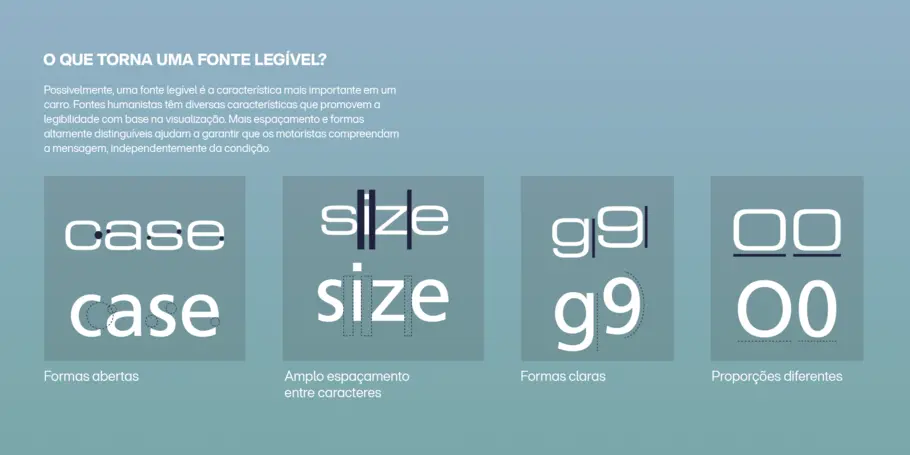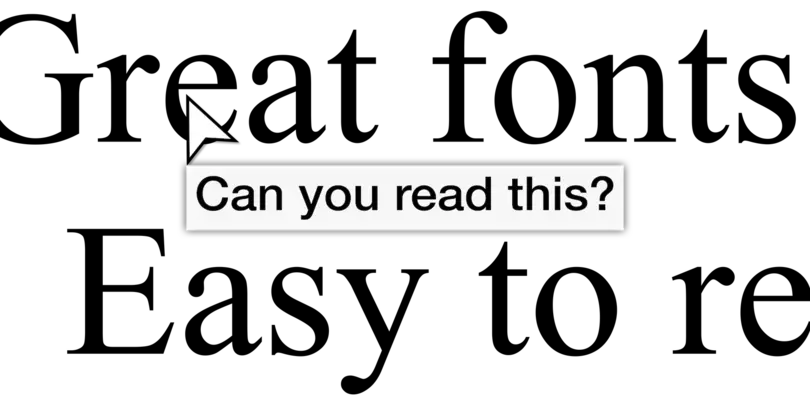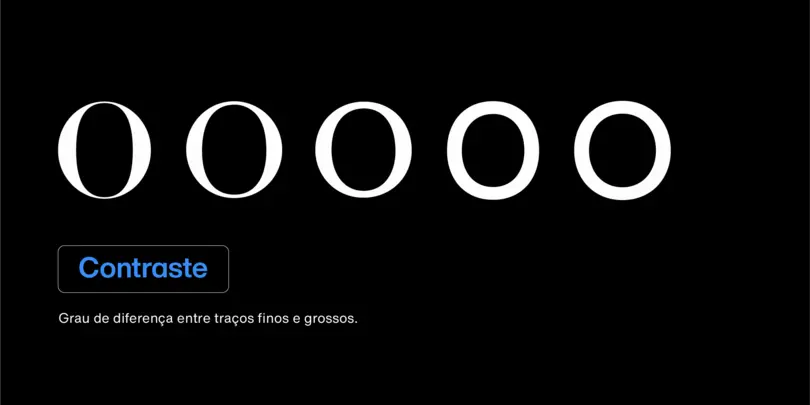
Como encontrar fontes legíveis.
“ Como muitas questões de design, a receita para essa resposta é uma mistura de arte e ciência e é regida por menos regras do que por melhores práticas. O segredo é compreender os principais componentes de uma fonte que afetam a legibilidade. ”
A legibilidade é uma consideração crucial ao tentar escolher uma fonte para o seu projeto. Veja como encontrar uma fonte legível que seja agradável aos olhos de seus leitores e clientes.
Recebemos muitas perguntas aqui na Monotype, mas uma das mais frequentes é provavelmente alguma variação disso: como encontro fontes legíveis? As pessoas podem perguntar de forma diferente — perguntarão quais fontes são mais legíveis, por exemplo, como saber se uma fonte é altamente legível — mas todos estão perguntando a mesma coisa básica: o que torna uma fonte legível e como faço para encontrar uma?
Como muitas questões de design, a receita para essa resposta é uma mistura de arte e ciência e é regida por menos regras do que por melhores práticas. A chave é compreender os principais componentes de uma fonte que afetam a legibilidade e, em seguida, encontrar a fonte com as características que melhor correspondem à linguagem visual com a qual você está trabalhando.
Legibilidade é um tópico amplo com muito mais nuances do que podemos abordar em um único artigo, mas compreender alguns pontos-chave ajudará você a escolher com segurança uma fonte legível para seu próximo projeto. Então, vamos nos aprofundar!
Easy to Read
A legibilidade está na mente do leitor.
Quando lemos, nossos olhos captam as formas escritas em uma página, traduzem essas formas em letras, combinam as letras em palavras e depois conectam essas palavras aos seus significados. Tudo isso acontece tão rapidamente que mal percebemos.
Mas, se uma dessas etapas do processo ficar mais lenta ou encontrar um obstáculo, nossa leitura também fica mais lenta. Isso pode não importar em alguns casos – uma manchete deliberadamente ofuscada em uma revista, talvez – mas é muito importante em casos de uso digital ou de rápida visualização, ou em ambientes de leitura estendida em que você deseja que o leitor mergulhe na história.
Fontes altamente legíveis essencialmente fogem da atenção do leitor. Elas são fáceis de serem examinadas pelos olhos e de compreensão pelo cérebro, de modo que o leitor é capaz de fluir pelas páginas de um livro ou verificar instantaneamente o texto na tela de um carro. Eles podem parecer tão naturais e fáceis quanto respirar.
O que torna uma fonte legível?
Certo, então a pergunta óbvia aqui é: o que torna uma fonte “fácil” para os olhos e o cérebro? Todas as fontes não são só… letras? Por que algumas cartas são mais fáceis de ler do que outras?
Ao procurar fontes legíveis, é útil pensar no formato das letras e das palavras (curiosidade: o termo para o formato da palavra é “bouma”). Na verdade, seus olhos e seu cérebro não traçam cada curva e ângulo de um “a” minúsculo antes de confirmar que, sim, é um “a” minúsculo. Talvez seja assim que funcionava quando você estava aprendendo a ler. Ainda assim, a maioria de nós ganha a capacidade de determinar que um “a” é um “a” com base na sua forma geral e na sua relação com as letras que estão ao lado.
Dito isso, as letras vêm em uma variedade de formatos, dependendo do estilo da fonte. O “O” em uma sem serifa geométrica, como ITC Avant Garde, é um círculo quase perfeito. Só um “a” poderia ser confundido, a princípio, com o mesmo “o”. Você consegue ler sans geométricos como Avant Garde ou Futura? Claro. Mas, muitas vezes, poderia ser mais fácil.
Insira fontes humanistas. Frederic Goudy. As fontes humanistas estão enraizadas na tradição caligráfica e, portanto, têm ecos na tipografia humanista (daí o nome) gravadas em seu DNA. Um exemplo popular de tipo humanista é Proxima Nova, de Mark Simonson. Olhe atentamente para o “o” e você verá que ele tem um formato oval sutil, não um círculo. Examine o “a” minúsculo e você notará que os traços na cavidade ficam mais finos à medida que encontram a haste vertical. Todos esses detalhes sinalizam a identidade da letra para nossos cérebros. Outras tipografias humanistas populares (e híbridos humanistas/geométricos) incluem Frutiger, Morandi, Gotham e Optima.
As fontes serifa oferecem legibilidade semelhante ao leitor, por isso não é surpresa que sejam a escolha predominante para livros, revistas e outras situações de leitura de formato longo. No entanto, as fontes com serifa têm historicamente representado um desafio em casos de uso digital devido ao contraste do traço, a diferença entre linhas grossas e finas em uma fonte (discutida abaixo). Fontes com serifa de alto contraste de traços com linhas finas são destinadas ao uso em tamanhos maiores, enquanto as serifas destinadas ao uso em tamanhos menores são projetadas com menos contraste de traços. Esse efeito e complexidade são frequentemente exacerbados pela qualidade da tela, o que torna as fontes com serifa mais difíceis de serem projetadas em casos de uso digital em que uma variedade de tamanhos pode ser necessária. Por causa disso, as tipografias humanistas se tornaram a escolha preferida para casos de uso digital e assim permanecem até hoje, embora as telas móveis modernas ofereçam clareza quase perfeita em fontes com serifa.
Um bom exemplo do oposto desses estilos é a fonte Eurostile. Não há nada de errado com o Eurostile como fonte e, na verdade, ela é incrivelmente popular em filmes de ficção científica por causa de sua vibe futurista (nos anos 70) e agora retro-futurista. Quando as montadoras começaram a implementar touchscreens e sistemas de infoentretenimento em seus veículos, muitas delas escolheram o Eurostile para a experiência do usuário desses sistemas. O Eurostile é amplamente baseado em letras quadradas que podem ser difíceis de distinguir umas das outras quando você tem apenas uma fração de segundo para observá-las. Como quando você está dirigindo um carro, por exemplo.
2001_eurostile_63_0
Características de uma fonte legível.
Encontrar uma fonte legível é uma questão que requer analisar muitos aspectos e, essencialmente, o objetivo é encontrar uma fonte que seja confortável de ler. Para os designers, o segredo é entender alguns detalhes essenciais que contribuem para uma boa legibilidade e, então, encontrar fontes que equilibrem esses fatores com a linguagem visual que você procura.
Contraste:
o contraste descreve a diferença entre traços grossos e finos em uma letra. Fontes com algum contraste são geralmente mais fáceis de ler porque a variação na largura do traço ajuda o leitor a distinguir entre letras que têm formatos comuns.
Dito isso, fontes com muito contraste podem acabar sendo bastante difíceis de ler fora dos usos de exibição. Uma fonte como Bodoni, com sua dinâmica espessa dramática e fina, cria um título impressionante. Mas esses traços finos e delicados praticamente desaparecem no tamanho do corpo do texto, tornando o tipo de letra praticamente impossível de ler.
Contraste
Altura-X:
a Altura-x refere-se literalmente à altura do x minúsculo em uma fonte, o que essencialmente determina a altura das letras minúsculas na fonte. Alturas-x maiores tendem a proporcionar melhor legibilidade porque o tamanho generoso torna as letras mais fáceis de ler.
No entanto, a altura-x muito alta pode confundir a distinção entre caracteres maiúsculos e minúsculos e até mesmo entre certos caracteres minúsculos (h e n, por exemplo). Alturas-x pequenas também podem proporcionar boa legibilidade, dependendo do design e do peso da fonte.
Espaçamento, kerning e crowding em geral:
o espaço entre as letras é tão essencial para a legibilidade quanto as próprias letras. Um r e n com kerner incorreto, por exemplo, podem facilmente parecer um m. O texto muito compacto em geral pode atrasar o leitor, e o texto muito solto pode aparentemente sair da página.
Algumas fontes são espaçadas e com kerner cuidadosamente pensado e precisam de poucos refinamentos adicionais, mas muitas exigirão ajustes cuidadosos quando colocadas no layout. O tipo legível deve parecer que respira e flui facilmente, guiando o leitor através de palavras e frases sem olhar duas vezes.
Durante o processo de descoberta, procure fontes em que as letras estejam conectadas, mas não aglomeradas e, se possível, investigue combinações de letras potencialmente problemáticas para problemas de kerning. Isso ajudará você a determinar quanto ajuste precisará fazer sozinho.
Dimensionamento óptico:
o dimensionamento óptico é a prática de projetar diferentes versões de uma fonte levando em consideração como e onde ela será experimentada. Essas otimizações podem incluir muito do que foi discutido acima – ajuste de espaçamento, altura-x, contraste do traço ou detalhes. Tamanhos maiores são projetados tendo em mente usos chamativos – manchetes ou até mesmo outdoors – e, normalmente, mostram os detalhes e sutilezas de um tipo de letra, ao mesmo tempo que espaçam adequadamente para escalas maiores. Por outro lado, os formatos das letras em fontes entre 3 e 7 pt são simplificados e exagerados para máxima clareza nesses tamanhos pequenos e, portanto, serão renderizados de forma limpa nas telas.
Nem todas as fontes têm tamanho óptico, mas vale a pena procurá-las se você quiser usar a mesma família de fontes em vários aplicativos e tamanhos.
Tamanhos ópticos da Helvetica Now
Os tamanhos ópticos da Helvetica Now permitem que ela funcione impecavelmente em várias aplicações, de textos grandes e atrativos a tipos micro extremamente legíveis.
Na dúvida, teste.
Depois de navegar pelas opções e selecionar algumas vencedoras em potencial, a etapa mais importante que você pode executar é testar. Ao fazer isso, lembre-se de que há uma diferença sutil entre legibilidade e fluidez. Se legibilidade é ser capaz de determinar a diferença entre caracteres, então espaçamento tem tudo a ver com o conforto da leitura. Se você tiver uma fonte muito legível e mal espaçada, ela não será muito fluída. Seu papel como designer é combinar o design da fonte (a fonte em si) e a tipografia (como ela é usada) em algo agradável para o leitor.
Então, defina um texto e veja se parece confortável. Existe uma variação saudável entre alto e baixo? Alguma palavra ou combinação de letras parece esmagada? Você se pega voltando para ler as frases uma segunda vez? Você pode até pedir a um amigo ou colega de trabalho que leia também.
Novamente, a legibilidade é uma mistura de arte e ciência e, na verdade, não existe uma fonte perfeita para a legibilidade. Mas com algumas práticas recomendadas básicas, além de sua visão e instintos, você pode encontrar algo que ofereça excelente legibilidade para seus leitores e usuários. Boa sorte!
Como encontrar fontes legíveis.